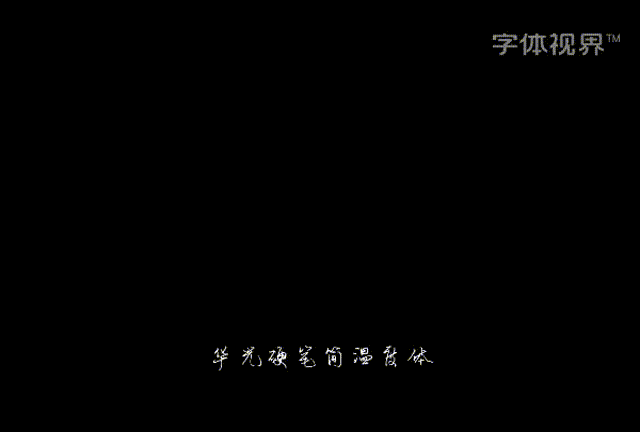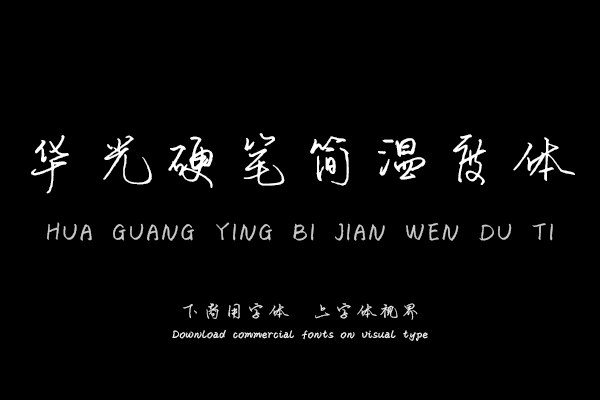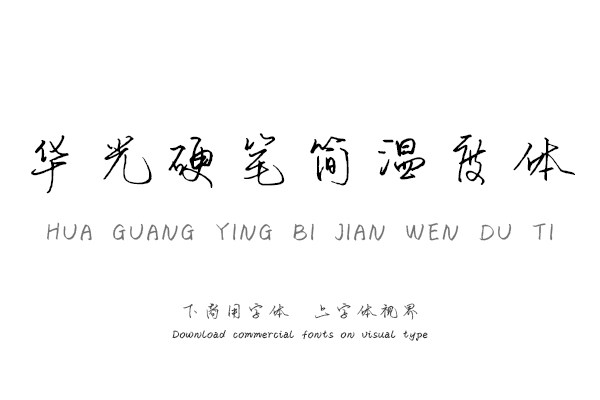
华光硬笔简温度体是一款传统书法字体,本字体笔画墨迹流畅,粗细变化自然,温柔个性,书法底蕴十足。本字体适用于正文排版,教学教育,广告宣传,包装等领域。购买须知:“下载服务费”与“字体VIP”所获得字体 仅用于个人非商用, 商用请联系付费授权。本字体为电脑用字,手机没有root权限不支持直接手机换字(手机如何root,请自行百度搜索教程)。购买前请先 了解清楚后再付款 ,字体为虚拟产品无法回收 一旦购买不支持退款。